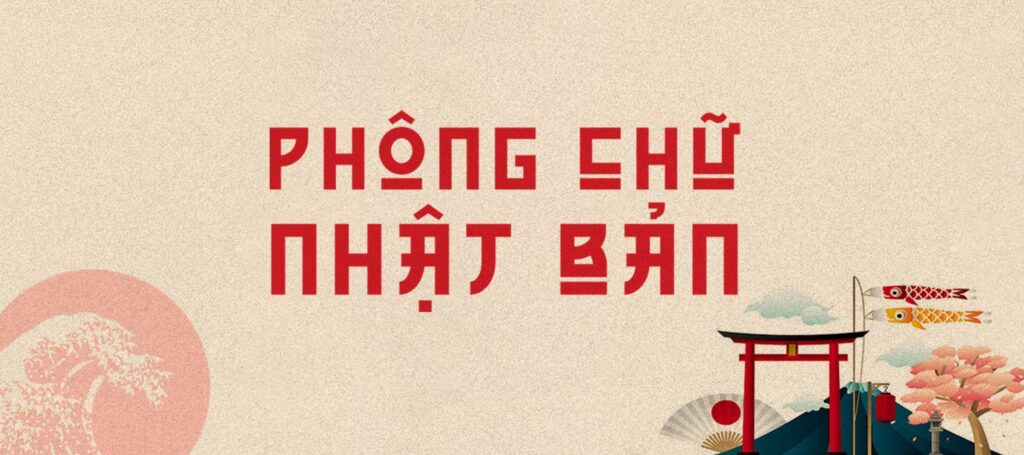
Font chữ Nhật Bản là nhóm phông chữ đặc thù được thiết kế dựa trên nguồn cảm hứng từ nghệ thuật thư đạo (Shodo), nghệ thuật gấp giấy Origami và tinh thần thẩm mỹ Wabi-Sabi của xứ Phù Tang. Sở hữu các đường vát nhọn mô phỏng nét chém tre, vệt cọ xước dứt khoát hoặc hình khối tối giản tinh gọn, font chữ phong cách Nhật Bản là chất liệu trực quan tuyệt vời để các kiến trúc sư, nhà thiết kế kiến tạo chiều sâu tĩnh tại cho các bản vẽ phối cảnh homestay phong cách Zen, quán trà đạo container hay biển hiệu nhà hàng ẩm thực Nhật.
Triết lý tối giản Zen và nét cọ thư đạo trong font chữ Nhật Bản
Điểm cuốn hút của font chữ kiểu Nhật Bản nằm ở sự tiết chế đường nét để tôn vinh khoảng trống (khoảng trống Ma), mô phỏng sinh động nhịp điệu đưa bút lông của các thiền sư. Các ký tự Latinh được tạo hình khéo léo với những nét gãy góc tựa như các nét sổ, nét phẩy trong chữ Hán (Kanji) và chữ mềm (Hiragana), mang lại cảm giác hoài cổ, trang trọng và đậm đà bản sắc Á Đông.
Sự ổn định về mặt cảm xúc của dòng font này giúp lan tỏa cảm giác an yên, tĩnh tại và sự tôn trọng thiên nhiên. Khi kết hợp cùng các vật liệu kiến trúc đặc trưng của phong cách Nhật Bản như gỗ sáng màu, vách nan tre nứa, sỏi cuội xám hay tường trát vữa thô trong các căn nhà lắp ghép sinh thái, phông chữ tạo nên sự hòa quyện thẩm mỹ nhẹ nhàng.
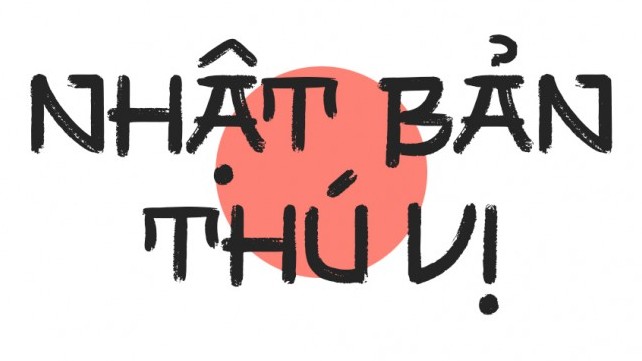
| Phân loại phong cách | Japanese Simulation / Zen Style / Brush & Geometric |
| Mục đích phù hợp | Biển tên quán trà, menu ẩm thực Nhật, logo homestay |
Tư vấn từ chuyên viên: Font Nhật Bản sở hữu nét tạo hình giàu tính bản sắc và cá tính hình khối mạnh. Để bản thiết kế đạt hiệu quả thẩm mỹ tốt, bạn nên sử dụng phông chữ này cho các tiêu đề chính, tên công trình hoặc các câu thiền ngữ ngắn.
03 Ứng dụng phông chữ phong cách Nhật Bản vào thực tế công trình
Nhờ diện mạo trang nhã và khả năng gợi nhớ văn hóa mạnh mẽ, bộ phông chữ này mang lại giá trị thực tế lớn trong khâu tạo điểm nhấn cho các công trình nghỉ dưỡng:
- Biển hiệu mặt tiền cho Quán Trà Đạo và Homestay phong cách Zen: Những nét chữ vát nhọn kiểu Nhật rất ăn ý khi gia công khắc chìm trên các thanh gỗ tuyết tùng hoặc bảng đá tự nhiên, mang lại diện mạo mộc mạc và thu hút những du khách yêu chuộng không gian thanh tịnh.
- Hệ thống biển tên phòng và Bảng chỉ dẫn Khu nghỉ dưỡng Onsen: Phông chữ này khi in trên rèm vải noren hoặc bảng gốm tráng men mờ sẽ giúp các căn phòng trong khu nhà lắp ghép toát lên nét duyên dáng, tạo cảm giác thư giãn cho du khách lưu trú.
- Bìa hồ sơ ý tưởng kiến trúc phong cách Japandi: Sử dụng font chữ kiểu Nhật Bản Việt hóa cho tên dự án giúp tập hồ sơ trông như một ấn phẩm mỹ thuật tinh tế, tạo thiện cảm lớn với các chủ đầu tư yêu thích sự kết hợp giữa kiến trúc Bắc Âu và tinh thần Nhật Bản.
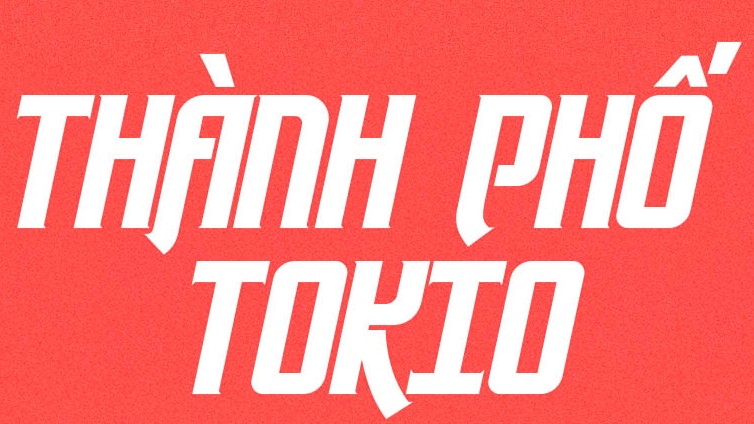
03 Lưu ý bố cục font chữ kiểu Nhật Bản duy trì nét tĩnh tại và rõ ràng
Để khai thác hiệu quả vẻ đẹp của dòng font đặc thù này mà không gây cảm giác khó đọc cho bản vẽ, người thiết kế nên lưu tâm một số kinh nghiệm sau:
- Chừa khoảng trống rộng rãi: Theo triết lý thẩm mỹ Nhật Bản, khoảng trống có giá trị ngang bằng với hình khối. Bạn nên để khoảng thở xung quanh tiêu đề thật thoáng đãng để các con chữ phát huy trọn vẹn vẻ đẹp thanh thoát.
- Tránh sử dụng cho văn bản dài: Cấu trúc mô phỏng nét chữ tượng hình của phông chữ Nhật Bản không phù hợp cho các đoạn văn bản giải thích kỹ thuật dài. Hãy giới hạn trong các cụm từ ngắn từ 2 đến 4 từ để tạo điểm nhấn thị giác tập trung.
- Kết hợp cùng gam màu tự nhiên thanh nhã: Phông chữ phát huy hiệu quả thị giác cao khi phối cùng các tông màu mang sắc thái tự nhiên như đen mực tàu, đỏ chu sa, xám đá cuội, xanh rêu hoặc trắng ngà trên nền gỗ thông sáng màu.